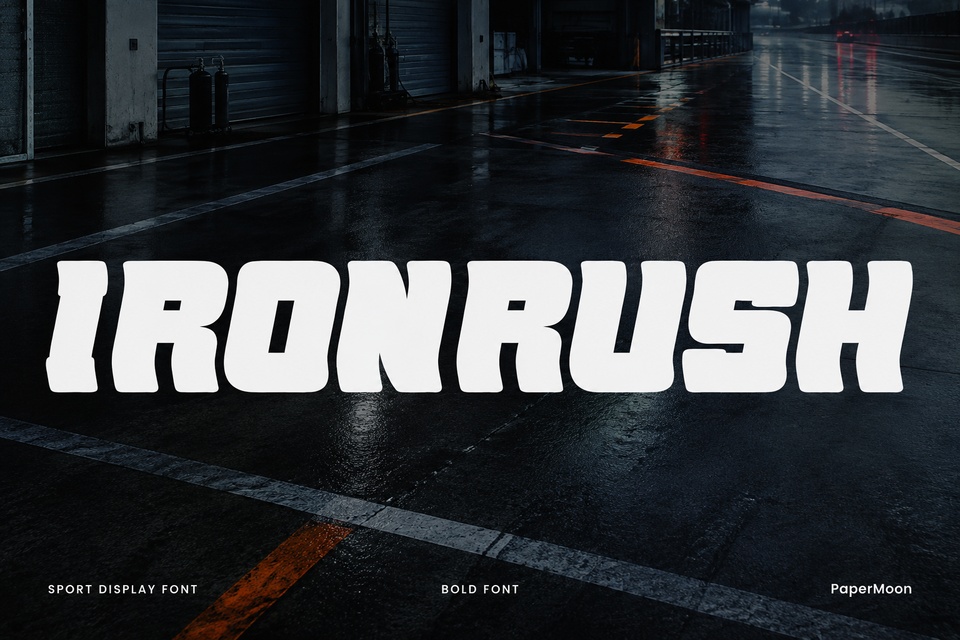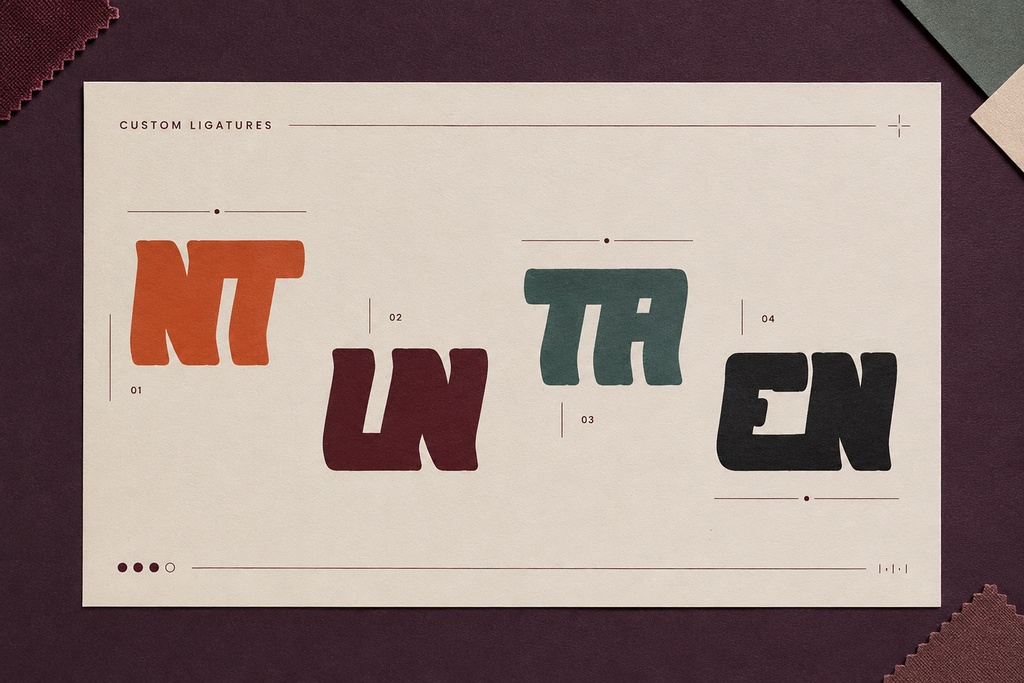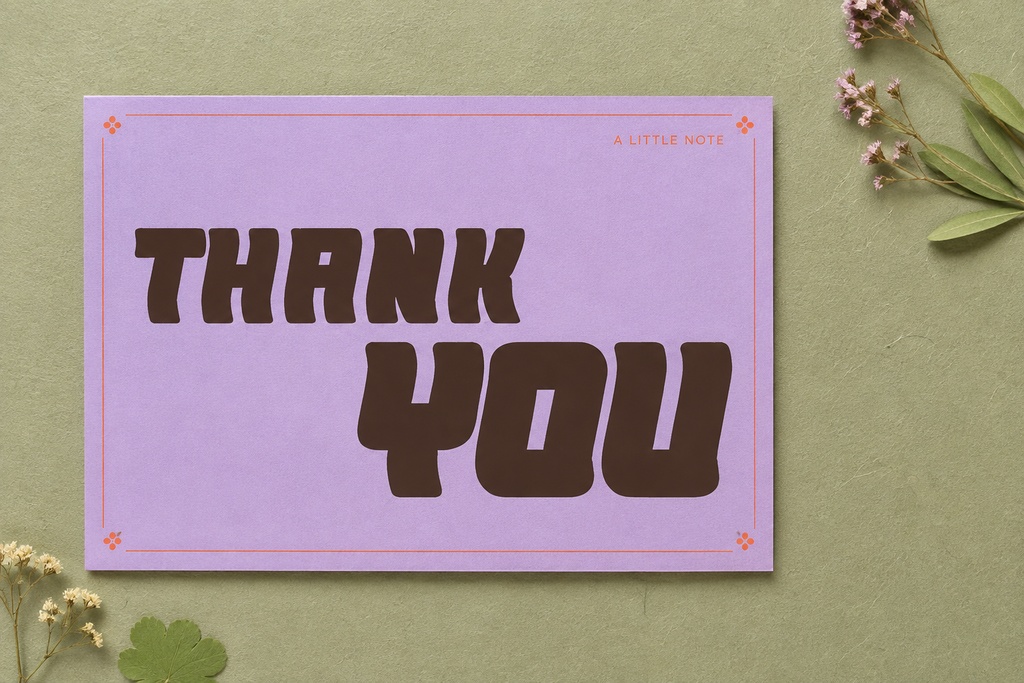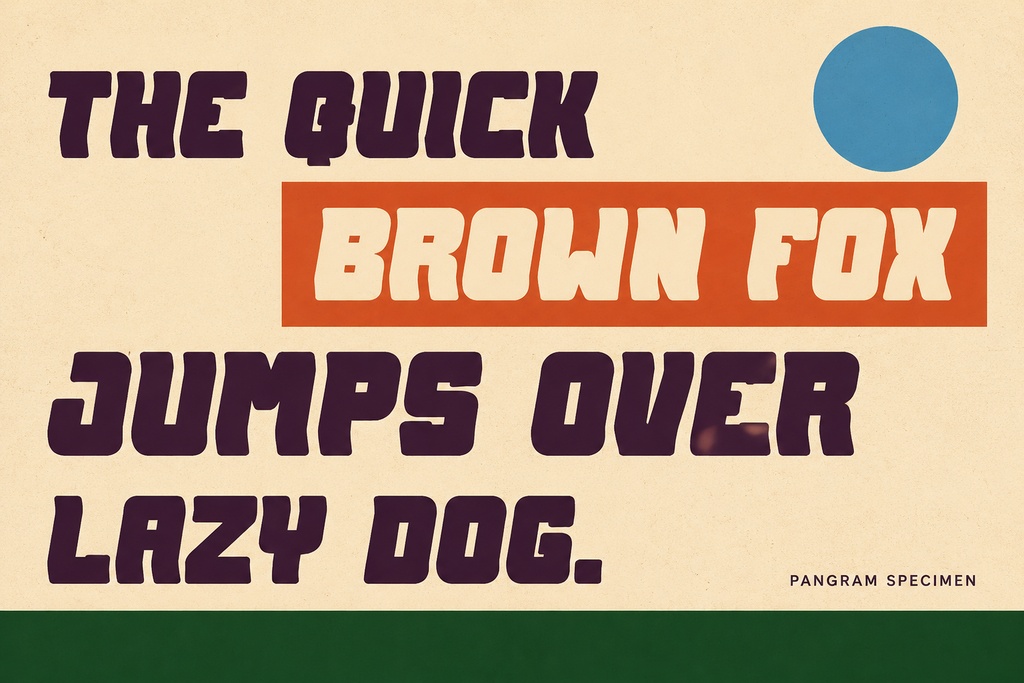
IronRush — ジムスポーツ用ディスプレイフォント
IronRushは、ジムやスポーツの世界のために作られた、力強くアスレチックなディスプレイフォントです。ウェイトリフティングのポスター、格闘技イベントのバナー、スポーツチームのユニフォーム、フィットネスアプリの起動画面など、あらゆる場面に最適な書体です。重厚で自信に満ちたストロークは、力強いエネルギーと力強さを湛え、遠くからでも一目でわかるインパクトのある見出しやロゴに最適です。ポスター、映画のタイトル、ライブのフライヤー、アルバムジャケット、ブランドマークなど、どんな用途にも使えるディスプレイ書体です。 この書体は、単一のRegularスタイルで提供されます。シンプルなスタイル構成で、大きなテキストでも最大限の視覚効果を発揮するように設計されています。OpenTypeカーニング(カーニング)と合字(リガ)に対応しているため、文字同士がぴったりと並び、よく使われる文字の組み合わせは滑らかでプロフェッショナルな仕上がりになります。ディスプレイ用途では、大きなサイズで表示されるため、文字間の隙間や重なりが目立つため、この緻密な間隔調整は非常に重要です。 主な特徴: 力強く、自信に満ちた、ジムやスポーツのエネルギーを感じさせる大胆な書体。 OpenType合字(liga)対応。文字ペアを連結することで、クリーンでプロフェッショナルな仕上がりを実現。 綿密なカーニング(kern)により、ポスターサイズでも崩れにくい、均一でタイトな文字間隔を実現。 OTF、TTF、WOFF、WOFF2形式に対応。デスクトップ、ウェブ、モバイルなど、あらゆる用途に対応。 PaperMoon 2026メタデータに対応。クリーンなOS/2フラグ(fsType=0、ベンダーPMON)で、商用利用にも対応。 最適な用途:ジムやフィットネスのブランディング、スポーツウェアやチームのロゴ、ポスターやイベントフライヤー、映画のタイトルやエンドクレジット、ライブポスター、アルバムカバー、製品ラベル、eスポーツやゲームのバナー、Tシャツやアパレルグラフィックなど、インパクトのある書体が必要なあらゆる場面で活躍します。 互換性:Adobe CC(Illustrator、InDesign、Photoshop)、Figma、Canva、Procreate、Affinity、Cricut Design Space、Silhouette Studio、および付属のWOFFおよびWOFF2ウェブフォントを介してあらゆる最新のウェブスタックで動作します。WindowsとMacの両方で簡単にインストールできます。 ライセンス:この商品はCubebrush商用ライセンスに基づき商用利用が可能です。クライアントワークや販売商品に、クレジット表記なしで使用できます。グリフのアウトラインは手書きで作成された書体で、AIによる文字生成は一切使用していません。そのため、商用プロジェクトで安心してご利用いただけます。 ジム、スポーツ、ディスプレイなどのプロジェクトに、本物の重厚感を与えましょう。IronRushをカートに追加して、デザインを始めましょう。